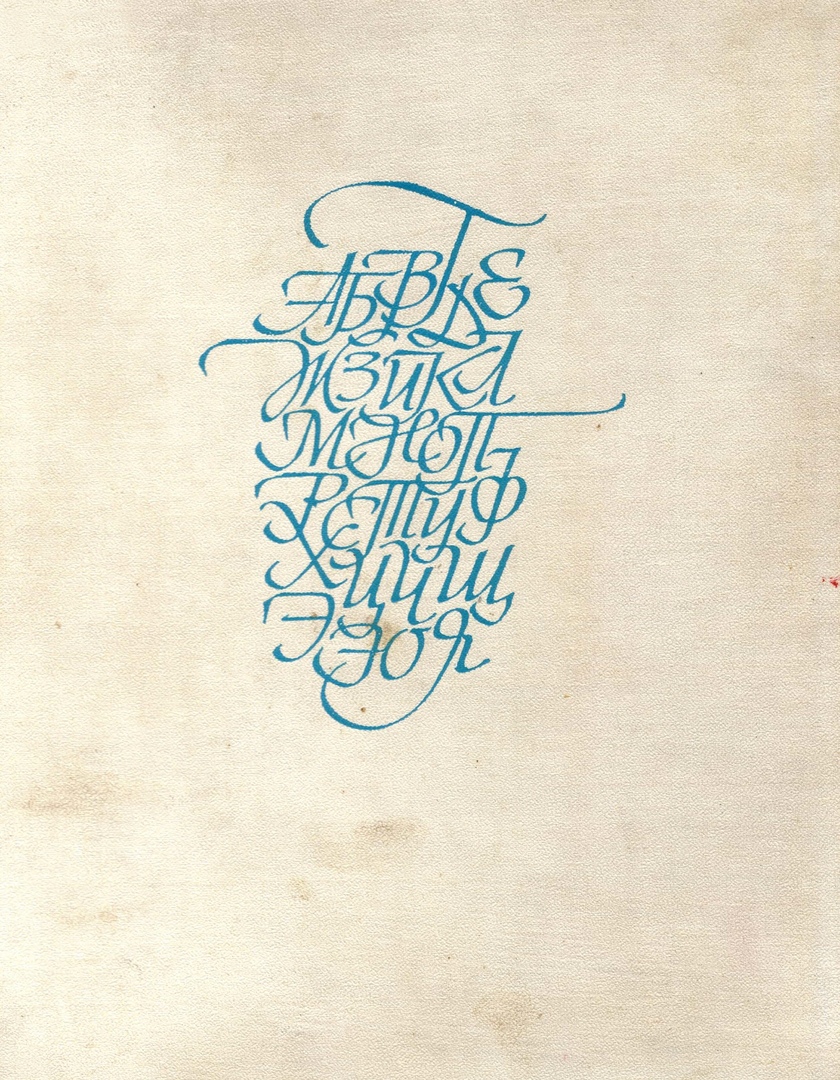
«Современный шрифт», Виллу Тоотс
Мы не представляем современную культуру без шрифта, и чем обширнее и разнообразнее становятся способы употребления шрифта, тем больше внимания мы должны уделять его качеству.
В книге уделяется внимание как писанию шрифта, так и его рисованию. Большое значение придается типографским шрифтам.
История шрифтов, техника рисования или письма и методика овладения тем или иным, разнообразие шрифтов и их назначение – все эти аспекты подробно рассмотрены в издании.